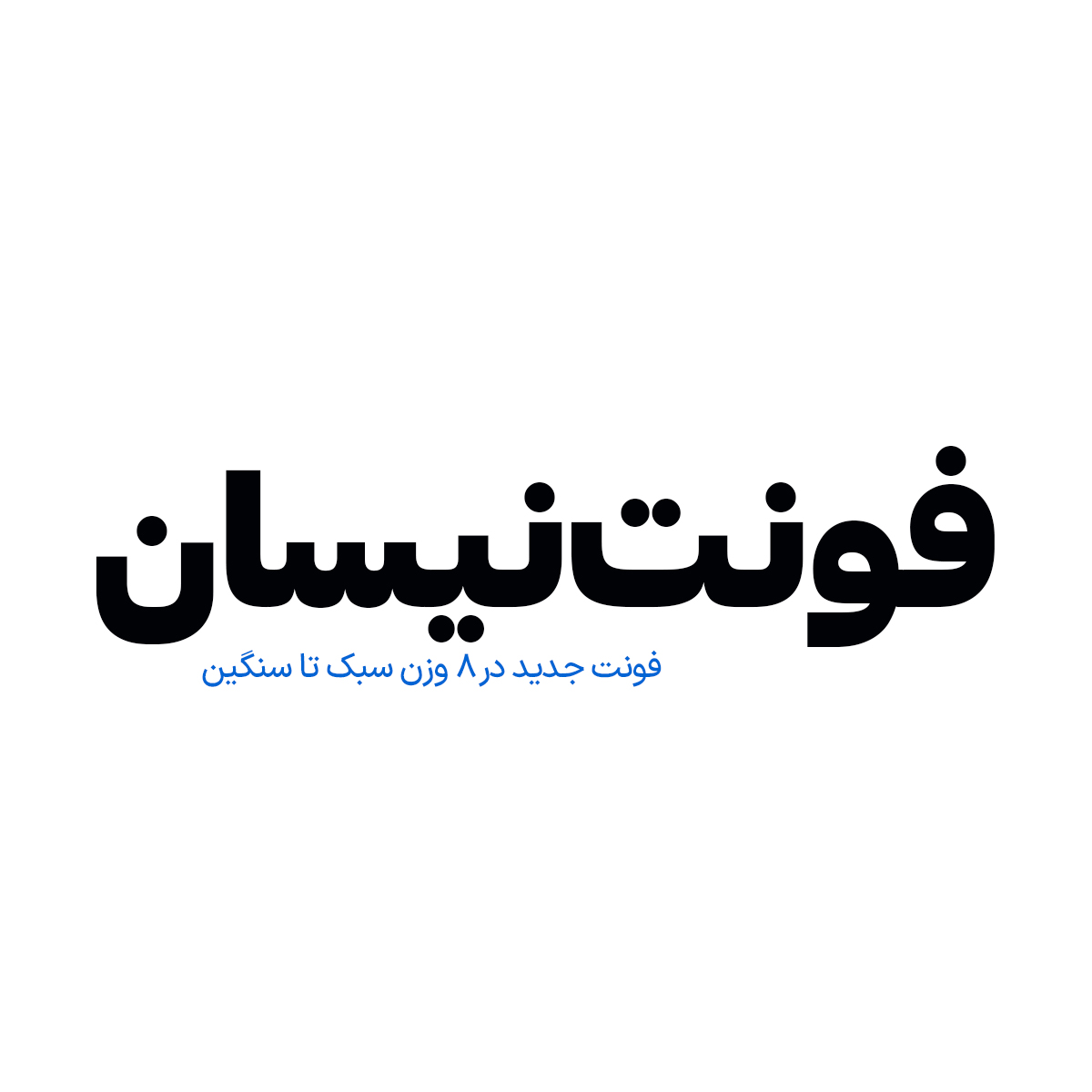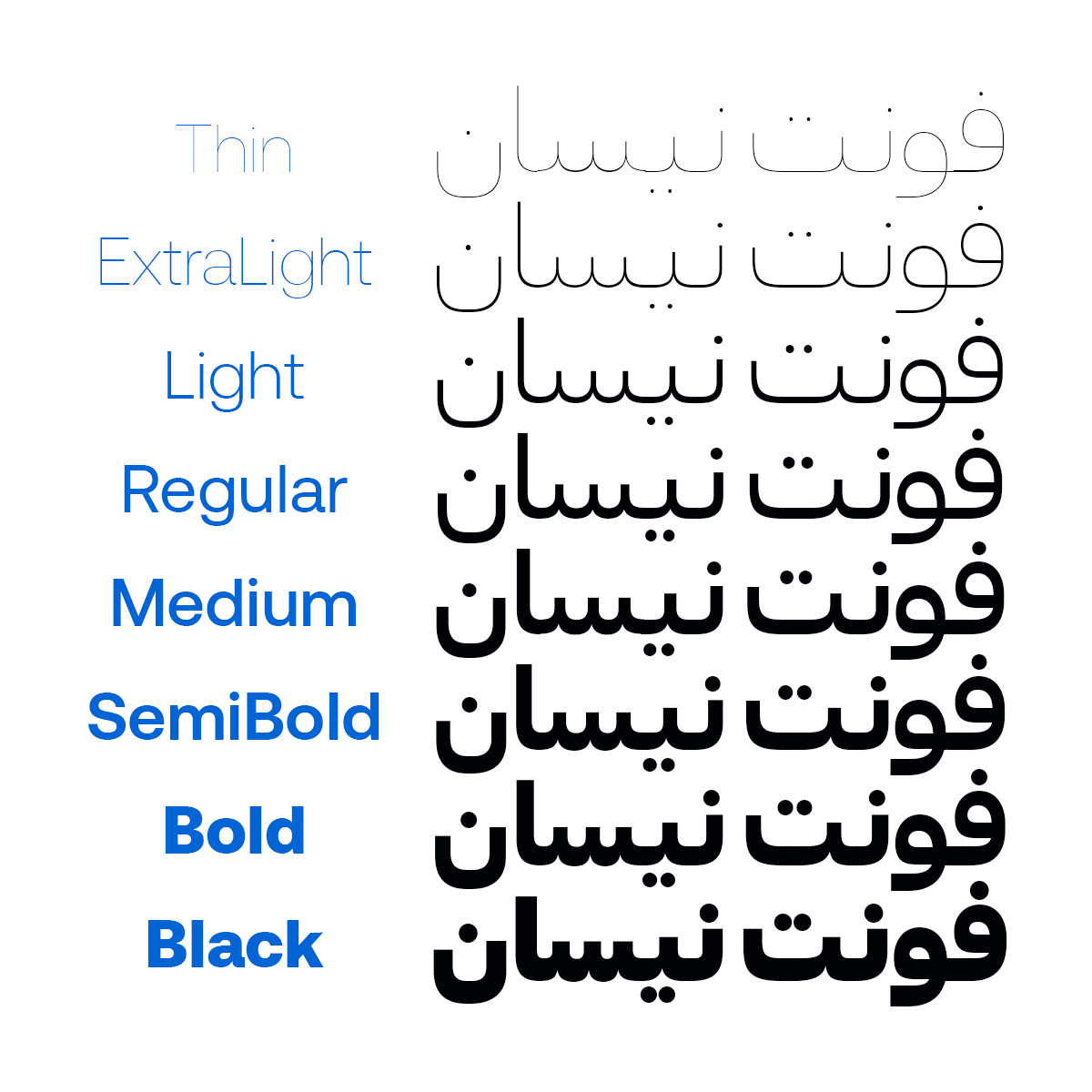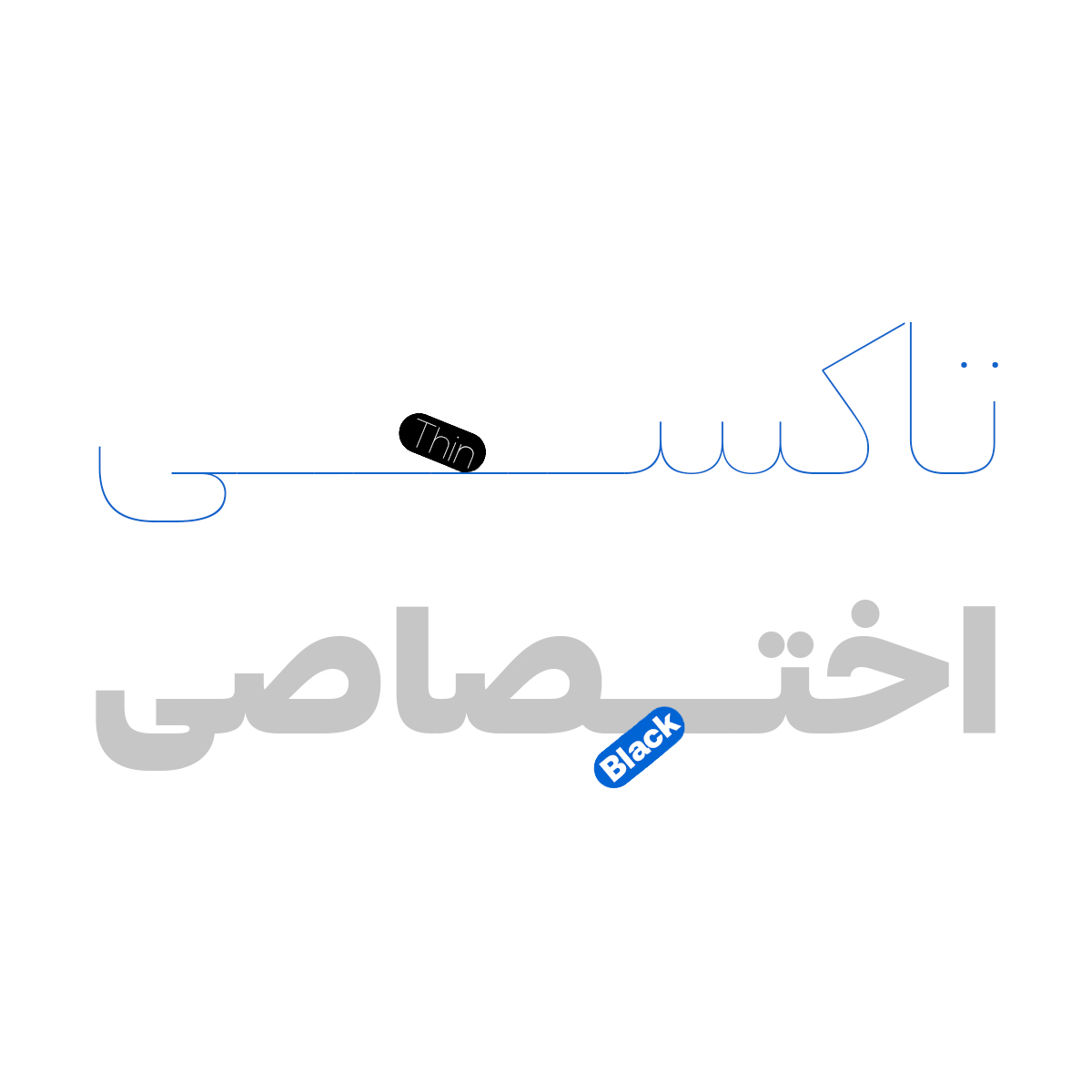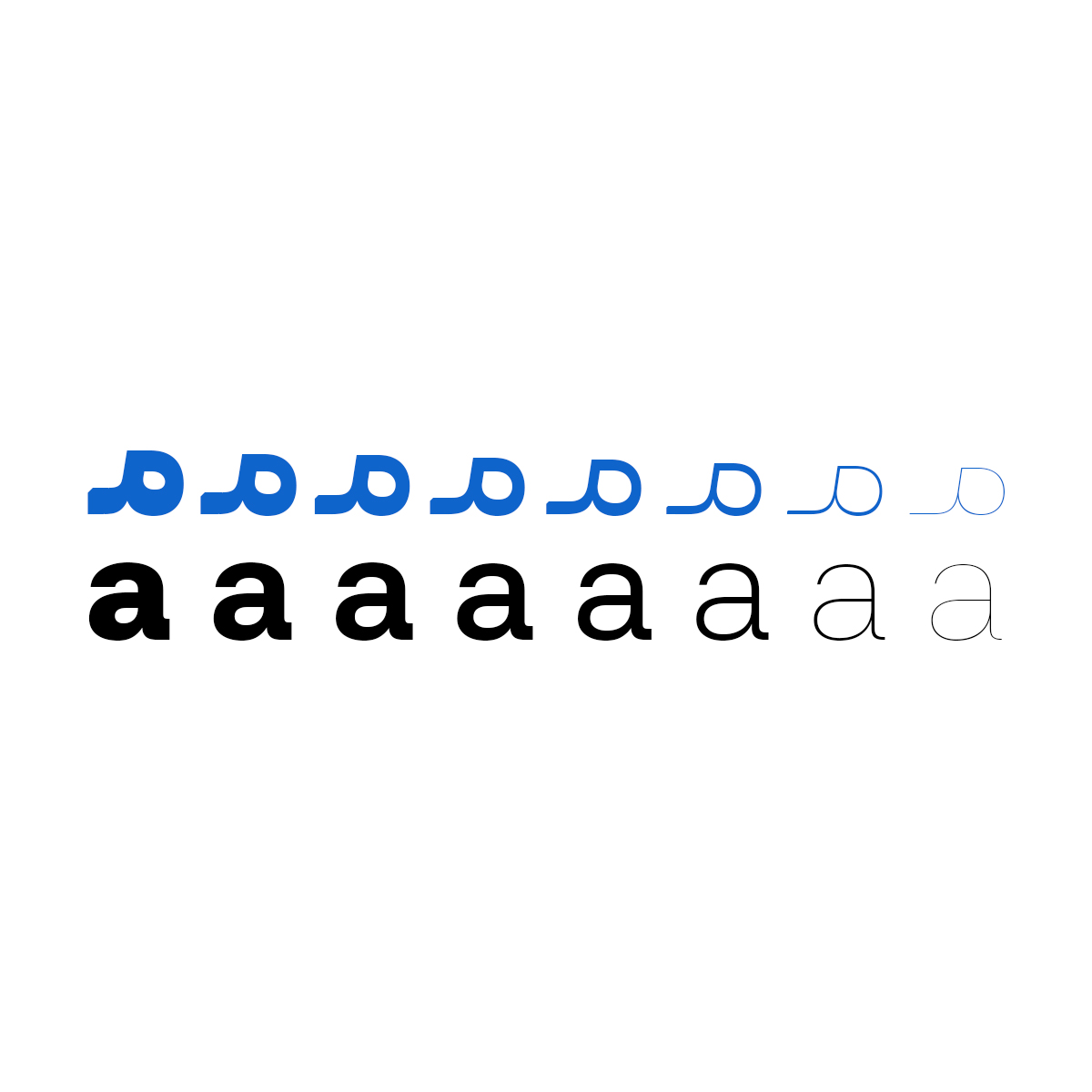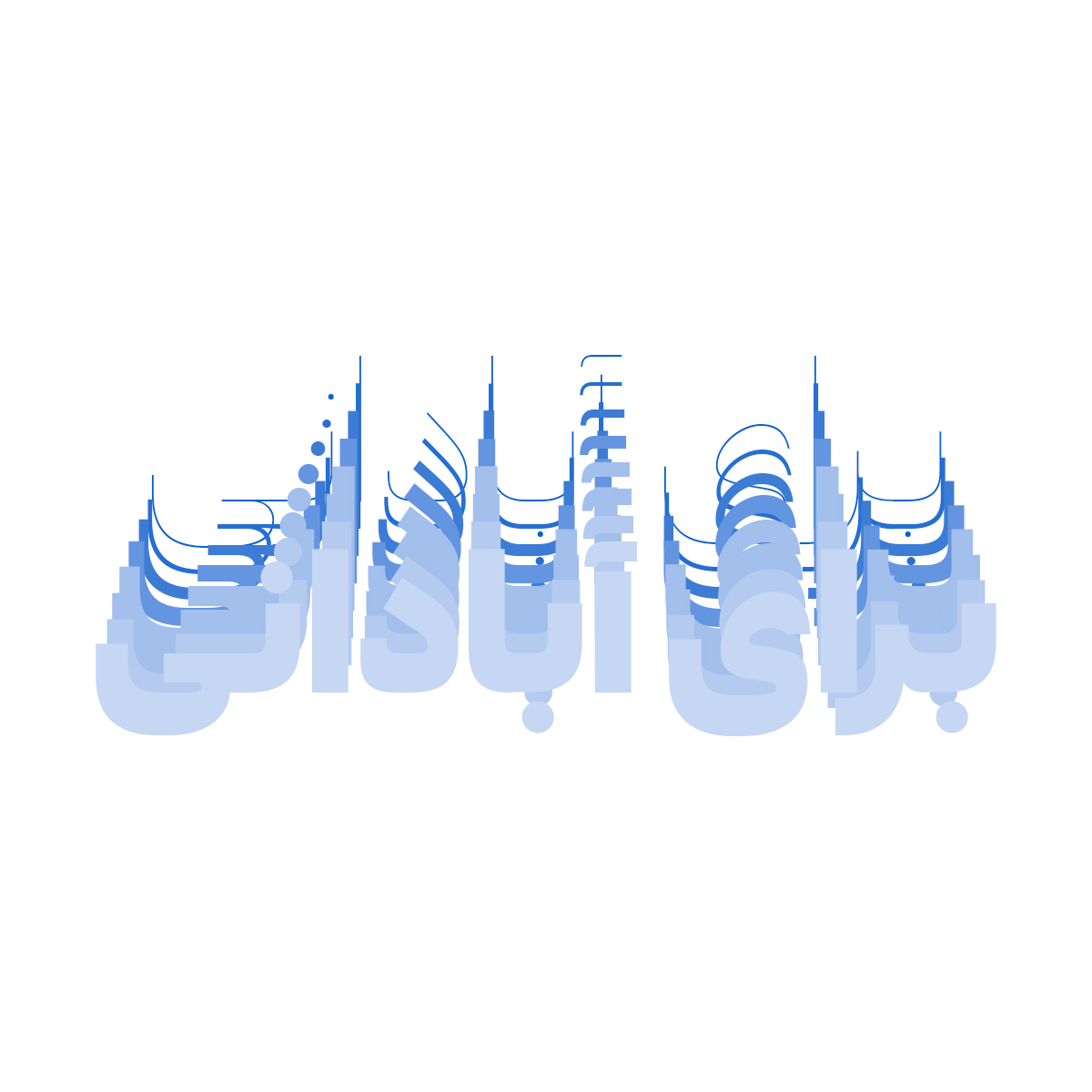
فونت فارسی نیسان Nissan Font
فونت فارسی نیسان یک فونت تایپ برای پروژههای فارسی می باشد و از همین روی برای استفاده در بیزینسها، استارتاپها و فضاهای الکترونیک مناسب است. خانواده…
فونت فارسی نیسان یک فونت تایپ برای پروژههای فارسی می باشد و از همین روی برای استفاده در بیزینسها، استارتاپها و فضاهای الکترونیک مناسب است. خانواده نیسان در بسته حرفهای خود، 8 وزن استاندارد از Thin تا Black را دارد که برای کاربردهای متنوع (از صنعت چاپ تا فضاهای مجازی) درنظر گرفته شده است. در ادامه برای شما نمونه تایپ های این محصول حرفه ای رو آماده کردیم که میتونید مشاهده کنید.
پیشنمایش و نمونه تایپ های فونت نیسان